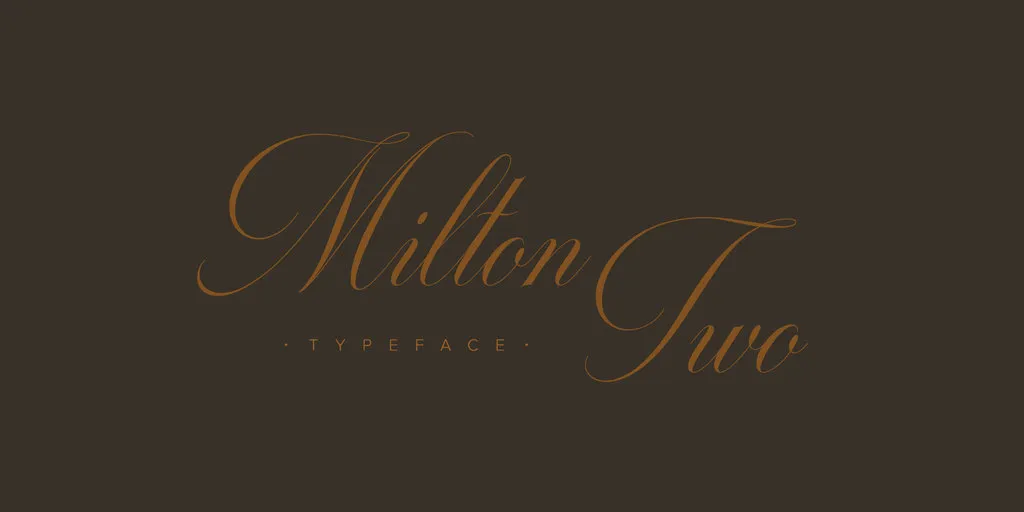
Milton Two Font Family – Download Grátis
Aqui está uma descrição para a página de download da fonte Milton Two Font Family: Agradecemos por seu interesse na fonte Milton Two Font Family. Esta elegante e única família de escrita é perfeita para um leque amplo de projetos, seja você designer gráfico, webdesigner ou criativo profissional que busca uma fonte casual mas sofisticada. Com seu estilo handwritten, a fonte Milton Two captura nuances sutis da escrita humana, o que resulta em um visual autêntico e único. Seu uso é intenso e ideal para nomes de empresa, websites ou materiais publicitários, onde deseja transmitir uma sensação descontraída e criativa. Com a fonte Milton Two, você terá todo o poder da escrita hand-drawn em seu projeto. A sua facilidade de uso garante que ela seja versátil e adaptável para qualquer aplicação do design. Com a fonte Milton Two Font Family, deixe-se envolver pela arte única dessa gradação especial. Para informações adicionais ou dúvidas, não hesite em entrar em contato conosco através de . Seu conhecimento é muito apreciado!